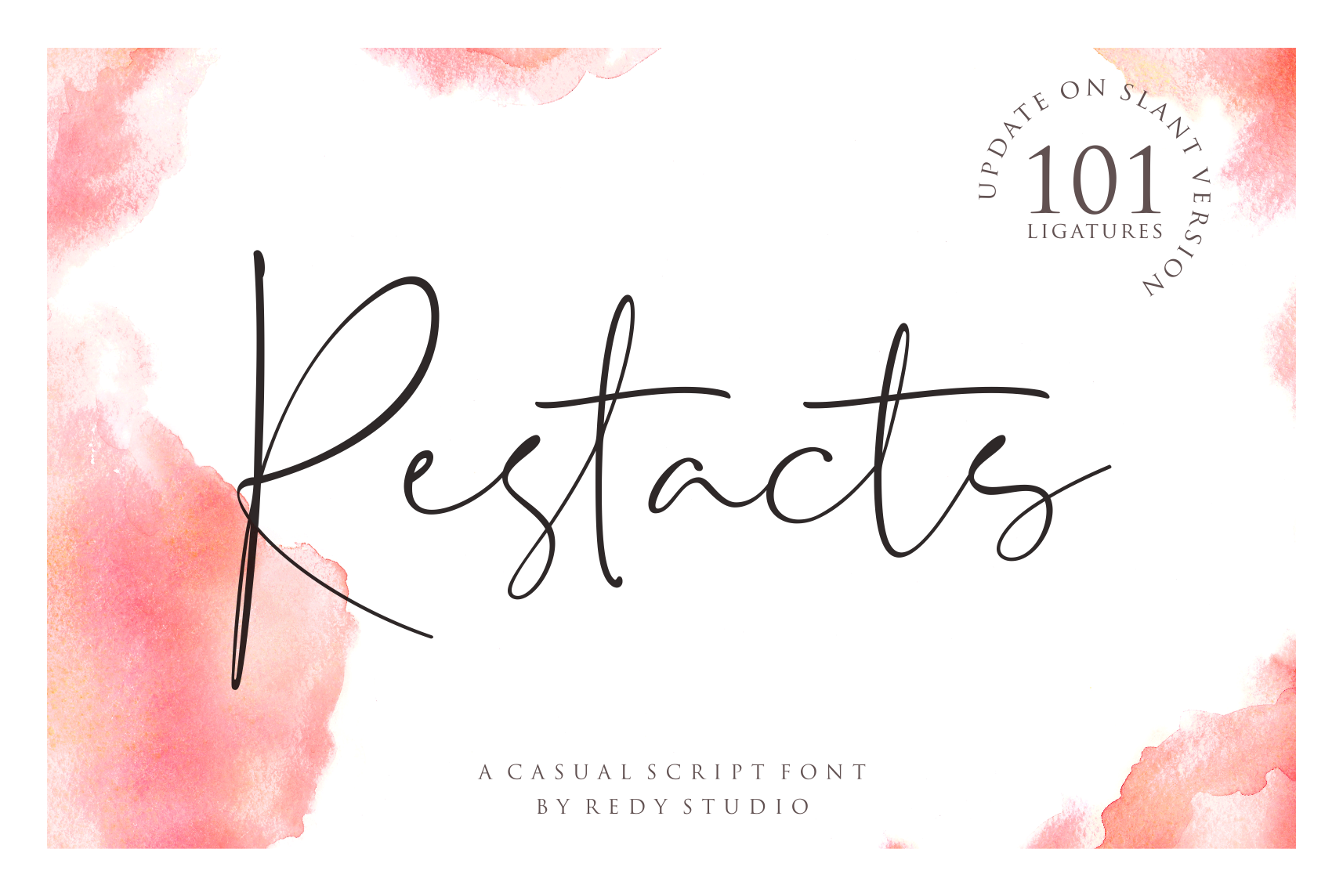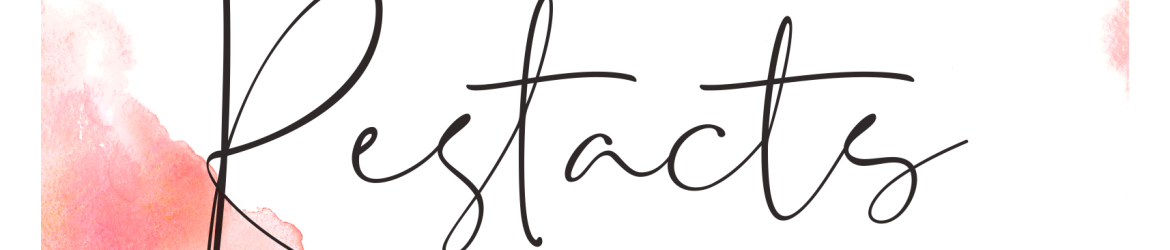
Restacts Handwritten Font – Download Grátis
A Restacts Script é uma fonte script elegante que oferece duas variações distintas para designers atentos ao detalhe. A primeira variante, chamada Restacts Script, traz um toque mais casual e feminino, ideal para projetos onde a estética leve e agradável é importante. Já a segunda variante apresenta uma tonalidade mais elegante e bold, perfeita para enfeites de fotografia, assinaturas de marca, cartões de casamento e criação de conteúdo para redes sociais. Restacts Script foi projetada com uma atenção cuidadosa ao detalhe, proporcionando um toque atraente nas letras, criando o impacto que você deseja em seu design. Estamos entusiasmados em oferecer essa fonte única como alternativa para quem busca uma combinação de elegância e feminilidade em suas criações digitais. O preview da fonte permite que você veja claramente os aspectos gráficos que destacam a Restacts Script, tornando-a um recurso valioso para qualquer projeto visual criativo. Nossa esperança é que essa fonte seja capaz de agregar valor ao seu trabalho, independente do tipo de projeto, como branding, redes sociais ou até mesmo quando você deseja adicionar um toque único e atraente à sua arte fotográfica.